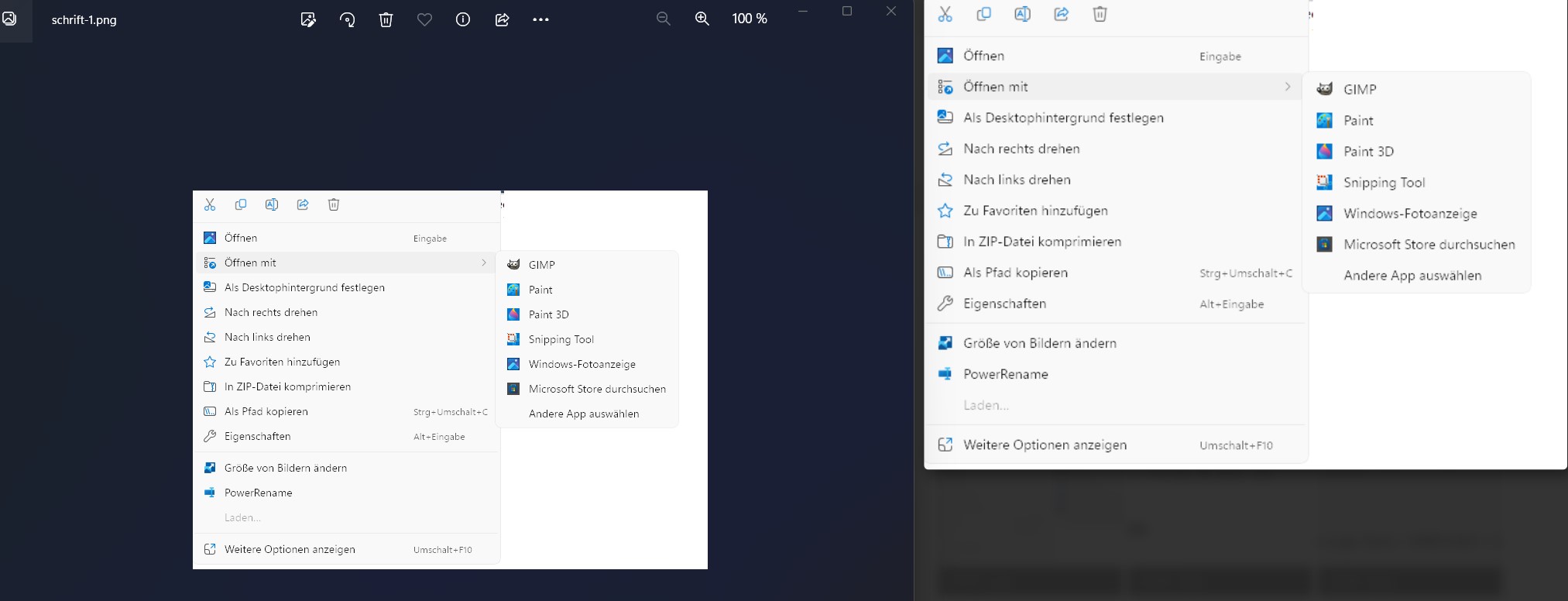
Schriftarten in manchen Anwendungen unscharf / krakelig
Ist bei mir genauso. Gewöhnt man sich daran.. habe auch schon alles mögliche versucht...ClearType, mit und ohne, diverse Einstellungen, auch die DPI unter 100% via Registry geändert nix. Wird nur besser wenn ich die Schrift bei mir um 6-10% vergrößere. Dann habe ich aber nicht mehr viel Platz in Anwendungen...alles ist zu groß und klobig.
Muss dazu sagen das meine native Monitorauflösung 1.366x768 beträgt, ist ein kleiner 18.5 Zoll. Wie gesagt, gewöhnt man sich dran.
Es reicht schon die "Bilder" einfach mal AN ZU KLICKEN !!
nein, das reicht leider nicht aus. totaler skalierungsmüll immer noch, schaut ebenfalls schrecklich aus.
naja, dass es erst durch abspeichern des bildes und dann öffnen auf 100% korrekt angezeigt wird. nicht durch das alleinige anklicken vom thumbnail wie @NatokWa behauptet, das ist schlicht und ergreifend falsch.
korrekt angezeigt zwar, aber die schrift ist trotzdem noch grauenhaft. sieht wie gesagt aus wie cleartype nicht richtig konfiguriert, da die buchstaben "scheckert" schwarz-grau sind.
der ist nicht zu klein mit 4k und 27 zoll ;) wird schon voll dargestellt.
aber guck mal den vergleich zu voll geöffnet im forum und runtergeladen auf 100%. da sind welten dazwischen. auch das runtergeladene bild auf 100% ist noch keine wirklich gute schrift, die ist immer noch nicht ganz korrekt.
auch hier mal auf dem desktop speichern und dann anschauen - dann sieht man es erst.
in der forenansicht auf volle größe gezoomt schaut es definitiv falsch aus.
nein, chrome läuft überall auf 100%.
nicht notwendig, es stand und steht immer auf 100% :D
Scharf ist es aber an den Kanten sind quasi Doppelkonturen sichtbar. Überwiegend an horizontalen Zeichen.
Das + Zeichen ist bei mir z.B. komplett verschwommen weil einfach zu klein für meine native Monitorauflösung. Früher hat Microsoft für nahezu jede gängige Auflösung optimierte Fonts, heute nicht, heut gibt es nur einen Font der skaliert wird. Leider ist das nicht überall optimal.
Problem ist schon länger bekannt
Um auf meine Frage zurückzukommen:
Ich habe mich als Admin angemeldet und siehe da, alles ist gestochen scharf, so wie es sein soll.
Liegt also wohl an meinem Standardbenutzer-Profil, das ich hauptsächlich nutze. Jemand eine Idee, wie ich das bereinigen / checken kann?